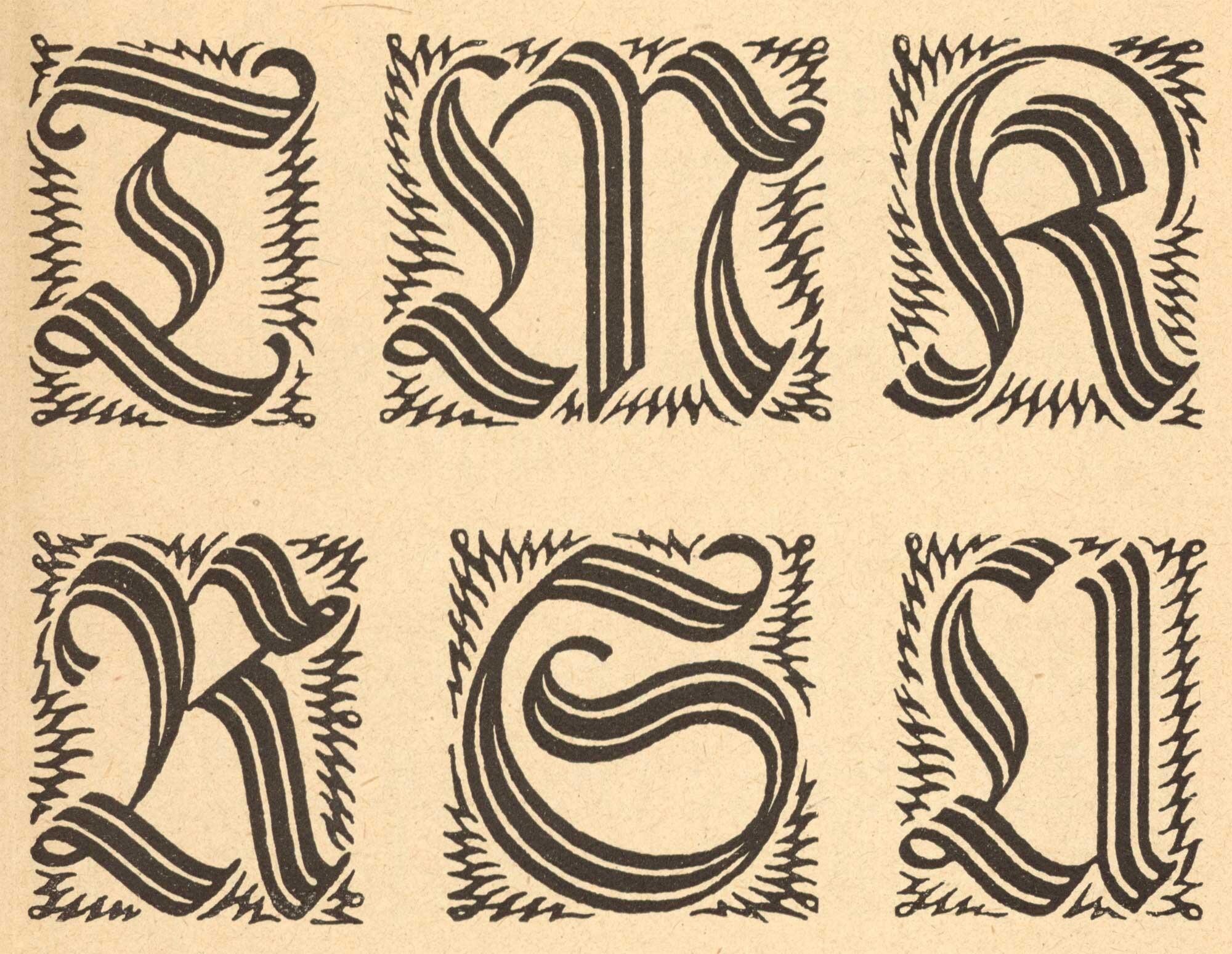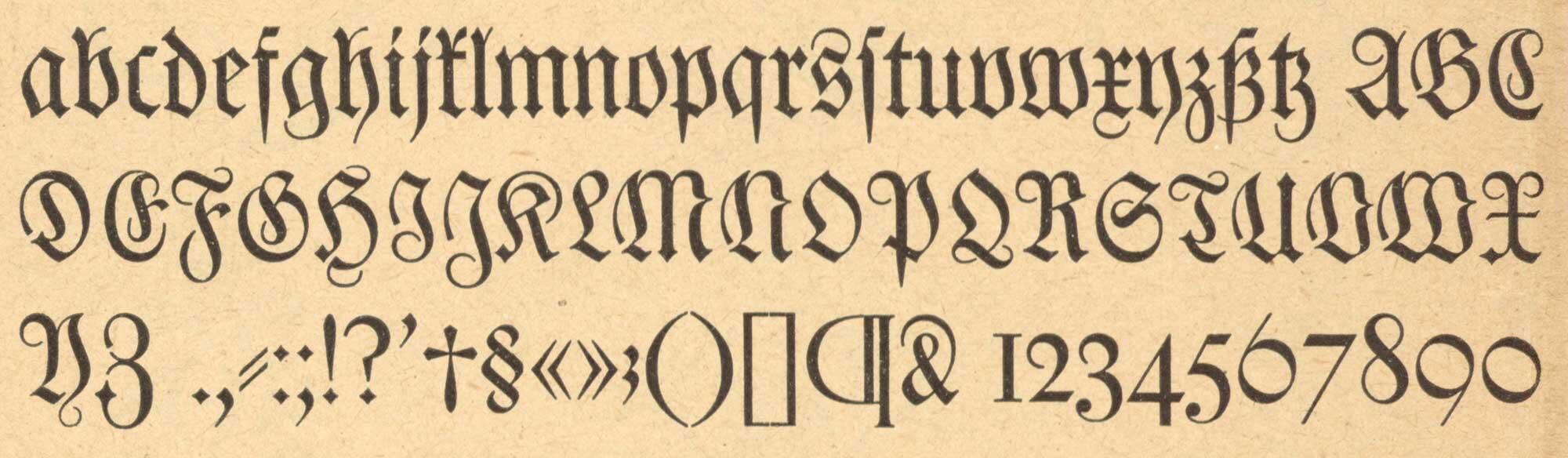
- 1912
- Gebrochene Schrift
Die Ehmcke-Fraktur von Fritz Helmuth Ehmcke erschien 1912 zunächst als Hausschrift der Offizin Drugulin in Leipzig. Ab 1919 wurde die Schrift dann über die D. Stempel AG angeboten und mit einem halbfetten Schnitt und Initialen weiter ausgebaut.
Eine Digitalisierung des mageren Schnitts gibt es von Gerhard Helzel. Von den Initialen gib es eine kostenlose Digitalisierung von Dieter Steffmann.